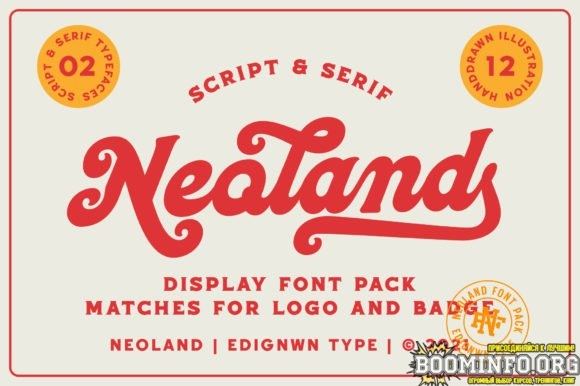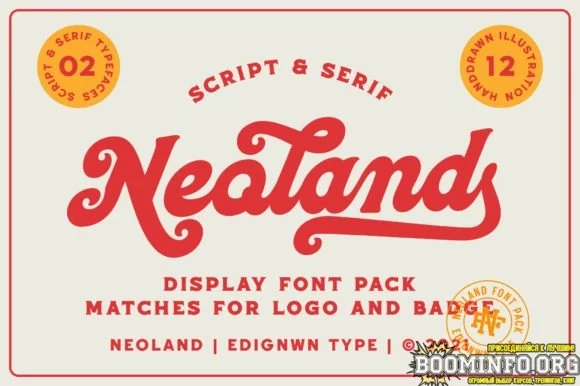
[Creativefabrica] Neoland Font (2021)
Название: Neoland Font (2021)
Neoland - великолепный и смелый шрифт трио (script, display, dingbats), созданный для придания стильности вашим заголовкам и логотипам.
Этот шрифт читается как сильный, уверенный и динамичный и может добавить тонны ностальгического характера в ваши проекты.